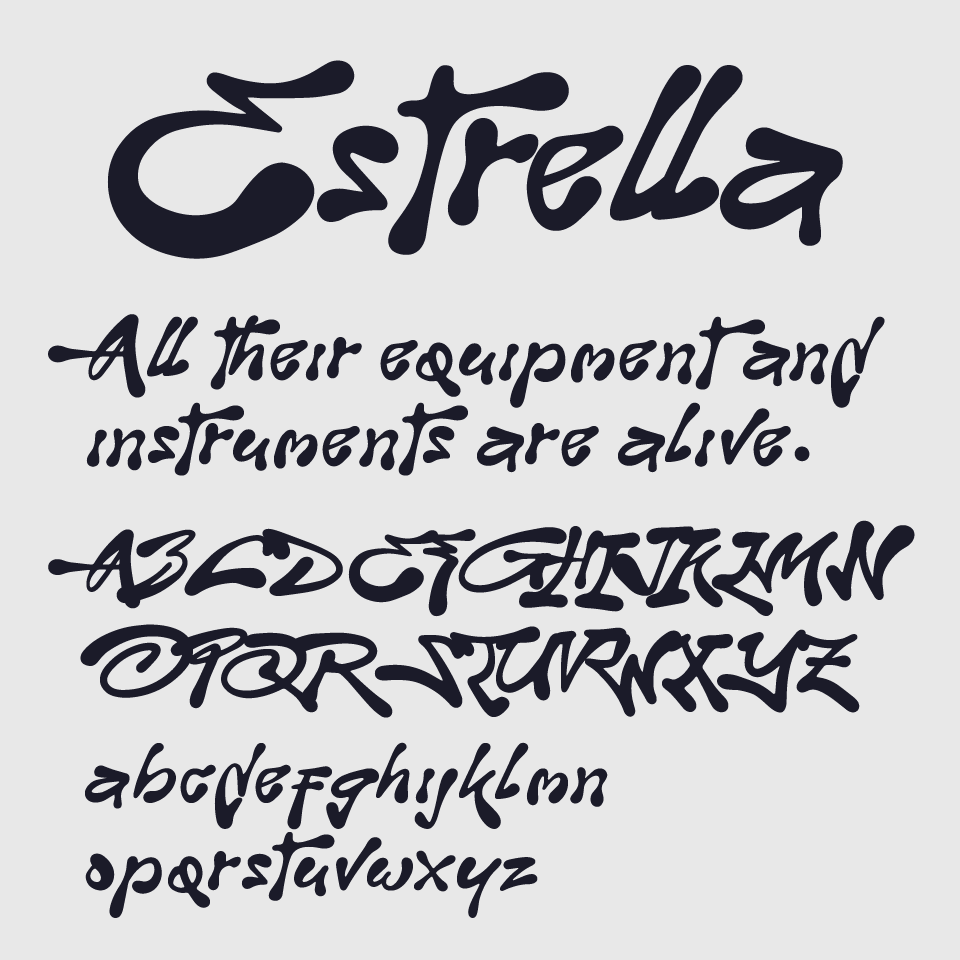
Estrellaフォントは、勢いと混沌をそのまま描いたようなグラフィティ感がたまらない手書きフォントです。
筆やスプレーで一気に描かれたような躍動感があり、文字ごとに表情が異なる奔放さが魅力です。読みやすさよりも、ストリートカルチャー感のある空気感を重視したデザインです。
グラフィティやヒップホップ、ロックなど、強いビートや衝動的なテーマに合います。タイポグラフィを主役にしたいときに効果を発揮し、作品に勢いや生々しさを加えたいときにぴったりなフォントです。